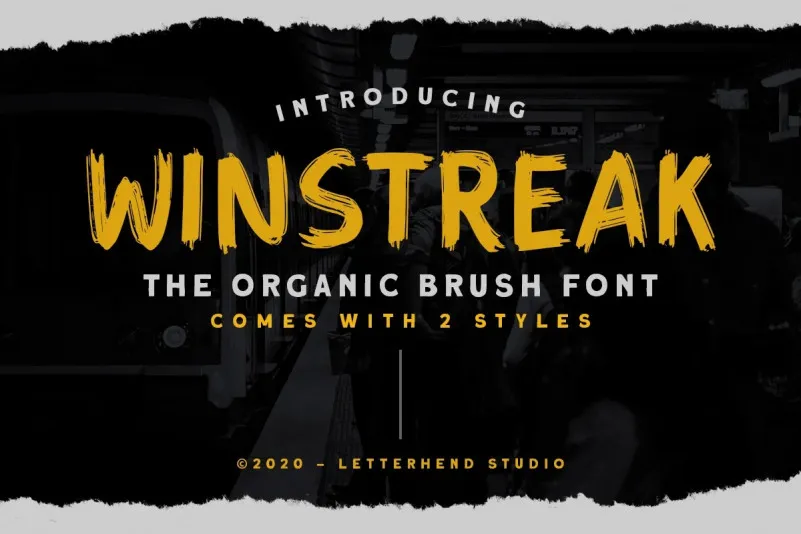
Winstreak Font – Fonte Grátis
Winstreak Font
A Winstreak Font é uma elegante fonte capilar criada para desfrutar do novo estilo moderno. Este belo tipo de letra em cauda grande e atraente foi projetado para ser aplicado na criação de logotipos, bem como outros formatos formais como cartões de convite, rótulos, revistas, livros, cartas de cumprimento ou cards de casamento, embalagens, maquiagem, material de escritório e livros. Essa fonte perfeitamente se adequa a quase qualquer propósito publicitário. Ela traz um ar sofisticado que certamente complementará qualquer projeto visando formalidade.